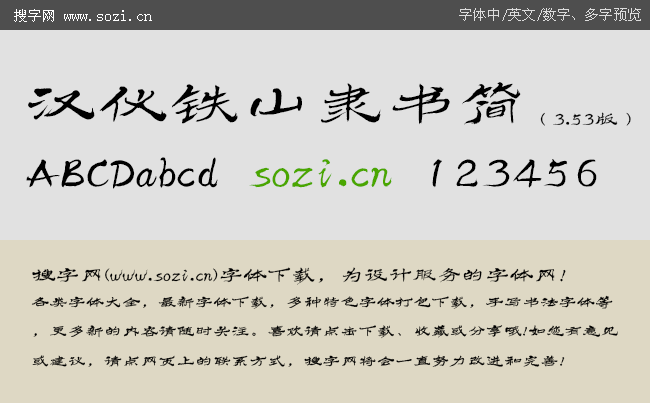
漢儀鐵山隸書簡(jiǎn)
搜字網(wǎng)提供一款漢儀鐵山隸書簡(jiǎn)中文字體下載,鐵山隸書承襲隸書方整不顯拘泥、變化卻無(wú)造作的高雅氣質(zhì);匯入何鐵山先生習(xí)書所悟之道,筆法挺勁秀美、重濁輕清,體勢(shì)開(kāi)張、點(diǎn)畫沉勁,別具豐潤(rùn)之姿?捎糜趫(bào)刊雜志排版,也適用于平面廣告,圖書印刷等廣告設(shè)計(jì)場(chǎng)合使用。